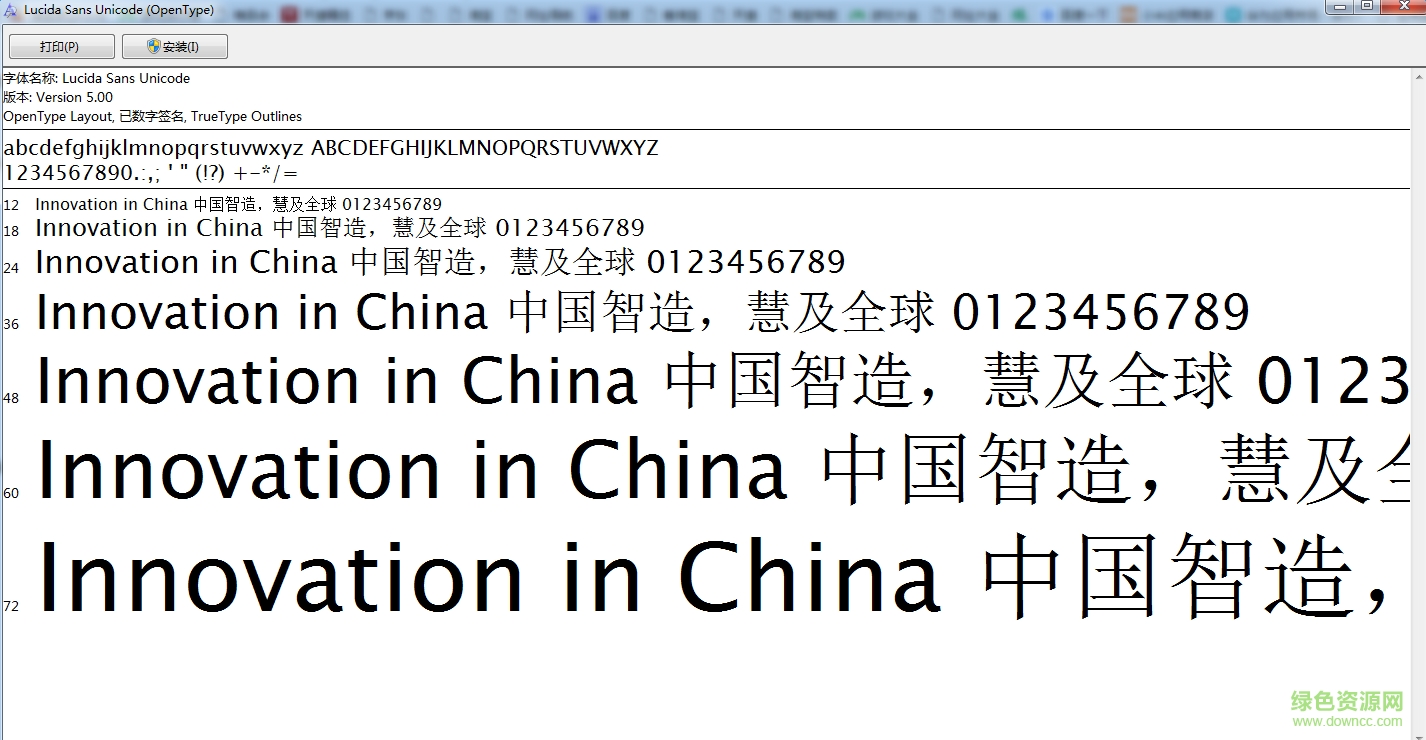
lucida sans unicode字體
古典體介紹
古典體或稱為人文主義體--(Johnston、Frutiger、Gill Sans、Lucida、Myriad、Optima、Segoe UI、Tahoma、Trebuchet MS、Verdana)。這些字體是無襯線字體中最具書法特色的,有更強(qiáng)烈的筆畫粗細(xì)變化和可讀性。